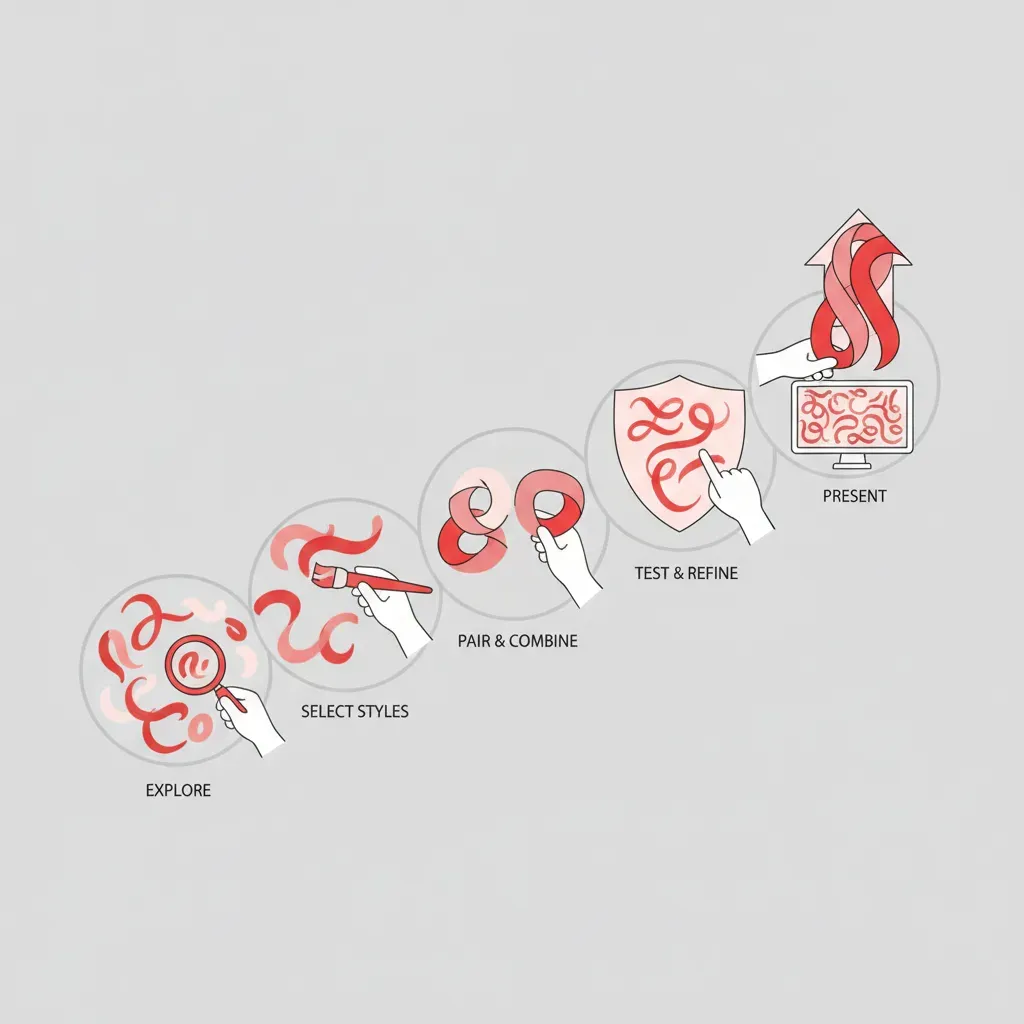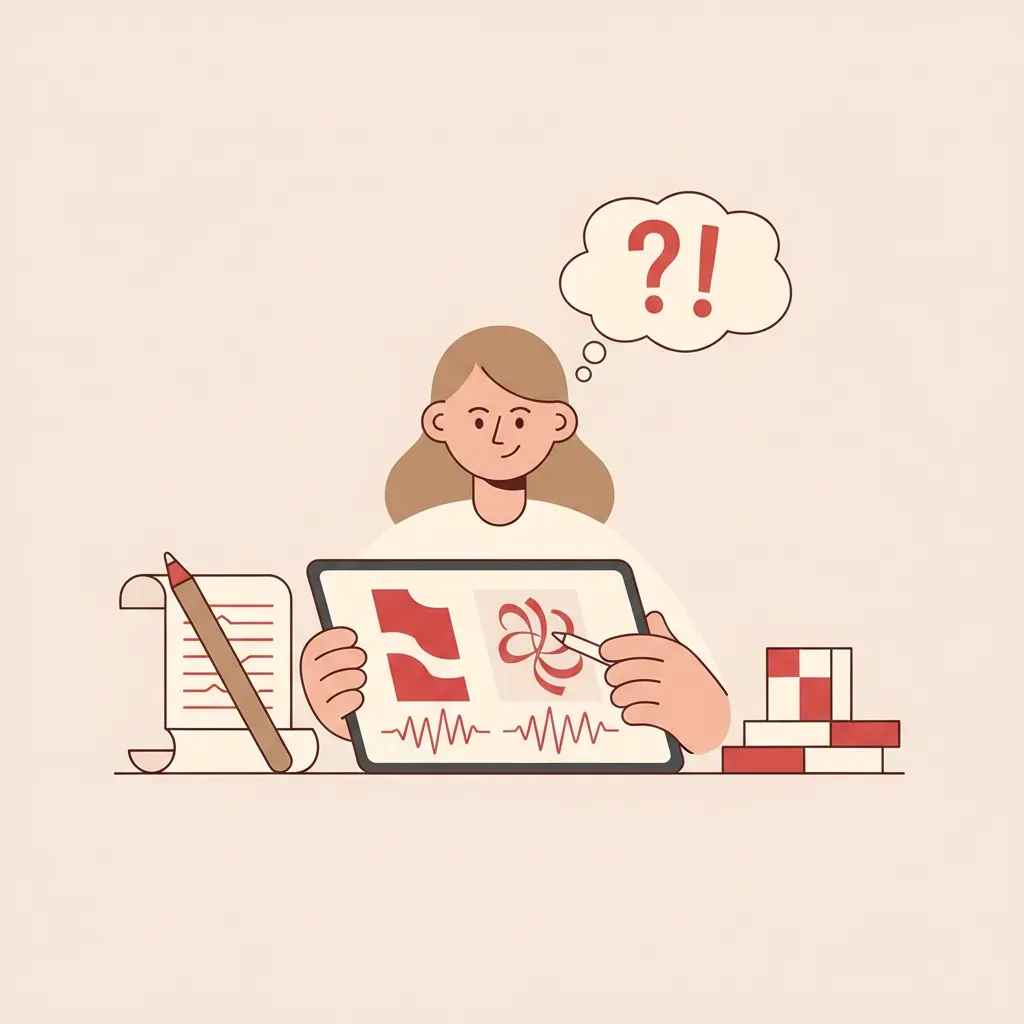
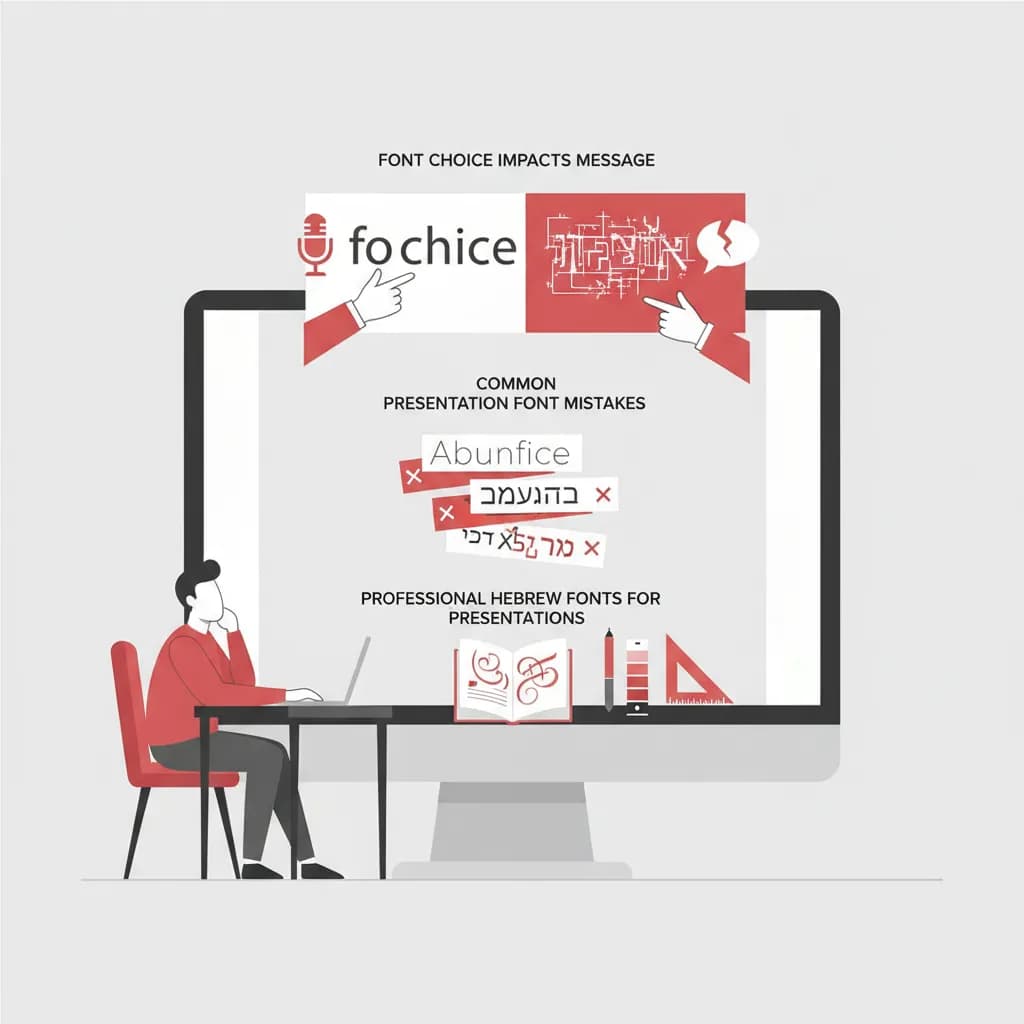
בחירת גופנים למצגת היא אחת ההחלטות הטיפוגרפיות המשמעותיות ביותר שמעצב גרפי יכול לקבל. הגופן שבוחרים משדר מסר רגשי ומקצועי עוד לפני שהקהל קרא מילה אחת – הוא מגדיר אם המצגת נראית אמינה, יצירתית, חמה או קרירה. גופנים למצגת שנבחרו נכון מגבירים את שיעור ההבנה של הצופים, מחזקים את הזהות הוויזואלית ומייצרים עקביות בין כל השקפים. לעומת זאת, גופן לא מתאים מפזר את תשומת הלב ומחליש את המסר המרכזי.
⚡ נקודות מפתח:
טיפוגרפיה היא השפה הוויזואלית של המצגת. גופנים למצגת לא נבחרים רק על בסיס אסתטיקה – הם נבחרים על בסיס המסר שהמצגת צריכה להעביר. גופן כבד ומרובע ישדר סמכות ויציבות; גופן כתב יד ישדר חמימות ואישיות; גופן גיאומטרי נקי ישדר חדשנות וטכנולוגיה.
בתחום פסיכולוגיה קוגניטיבית ידוע כי הצורה החזותית של טקסט משפיעה על האופן שבו הקורא מעבד מידע. כאשר בוחרים גופנים למצגת שמתאימים לתוכן, הקהל מעבד את המסר בצורה חלקה יותר ומרגיש שהמציג מוכן ומקצועי. כאשר הגופן "נלחם" עם התוכן – למשל, גופן שובבני במצגת פיננסית רצינית – נוצרת דיסוננס קוגניטיבי שמפריע לתקשורת.
לבחירת גופנים למצגת בעברית יש שיקולים נוספים: עברית נכתבת מימין לשמאל, ולא כל גופן מעוצב עם מנגנוני ניקוד מלאים או תמיכה בכל הסימנים הנדרשים. לכן חשוב לבחור גופן שתוכנן מלכתחילה לשפה העברית, ולא גופן לועזי שעבר התאמה חלקית.
בחירת גופנים למצגת צריכה להיות תהליך מובנה, לא אינטואיטיבי בלבד. להלן תהליך מעשי שמאפשר לקבל החלטה מושכלת:
שלב 1: הגדירו את אופי המצגת
לפני שפותחים כלל את ספריית הגופנים, שאלו: האם המצגת היא עסקית-פורמלית, אקדמית, קריאטיבית, או חינוכית? מצגת לדירקטוריון דורשת גופן שמשדר אמינות ויציבות. מצגת לסטארטאפ יכולה להרשות לעצמה גופן יותר חדשני ומרענן.
שלב 2: בחרו גופן כותרות ראשי
גופן הכותרות הוא זה שמייצר את הרושם הראשוני. הוא יכול להיות ייחודי, דרמטי, או עם אופי בולט. לדוגמה, למצגות עם אווירה מיוחדת, פונט דיפלומט מציע איזון בין יוקרה קלאסית לנגיעות מודרניות, עם משקלים מרובים שמאפשרים גמישות עיצובית.
שלב 3: בחרו גופן גוף קריא ופשוט
גופן גוף הטקסט חייב להיות קריא בגדלים קטנים יחסית ועל מסכים שונים. גופנים מסוג sans-serif – כלומר, ללא תגים בקצות האותיות – מתאימים במיוחד לטקסט גוף במצגות דיגיטליות, כיוון שהם נקיים ומדויקים על מסכי LED. גופנים עם סריף מתאימים יותר לדפוס.
שלב 4: בדקו ניגודיות ונגישות
גופן לבן על רקע בהיר, או גופן כהה על רקע כהה – שתיהן טעויות שמקשות על הקריאה. בדקו שיש ניגודיות מספקת בין צבע הגופן לצבע הרקע. לצורך נגישות, מומלץ להשתמש ב-Google Fonts כמשאב לגופנים מאושרים לנגישות.
שלב 5: בדקו עקביות לאורך כל המצגת
לאחר שבחרתם את שני הגופנים, עברו על כל שקף וודאו שהם מיושמים בעקביות. כותרות תמיד בגופן אחד, גוף טקסט תמיד בגופן השני. עקביות טיפוגרפית יוצרת תחושת מקצועיות ומאפשרת לקהל להתמקד בתוכן ולא בעיצוב.
מעבר לבחירת הגופן עצמו, ישנן מספר עצות מעשיות שמשדרגות משמעותית את השימוש בגופנים למצגת:
לדוגמה מעשית: מצגת עסקית שמציגה תוצאות כספיות לדירקטוריון תרוויח מגופן כמו פונט אופטימיסט בכותרות – גופן כתב יד חינני שמשדר חיוביות ומרומם, ומשלב אותו עם גופן sans-serif נקי לגוף. הניגוד בין השניים יוצר עניין ויזואלי מבלי לפגוע בקריאות.
צ'ק-ליסט מהיר לפני הגשת המצגת:
גם מעצבים מנוסים נופלים לפעמים לאותן מלכודות טיפוגרפיות. הנה הטעויות הנפוצות ביותר בבחירת גופנים למצגת ואיך להימנע מהן:
טעות 1: שימוש ביותר מדי גופנים שונים
שימוש בשלושה, ארבעה או חמישה גופנים שונים בגופנים למצגת אחת יוצר כאוס ויזואלי שמסיח את הדעת מהתוכן. הכלל הבסיסי: מקסימום שני גופנים – אחד לכותרות ואחד לגוף. אם רוצים גיוון, השתמשו במשקלים שונים של אותה משפחת גופנים.
טעות 2: בחירת גופנים למצגת שאינם מותקנים על מחשב אחר
גופן שמותקן על המחשב שלכם עשוי להיות מוחלף בגופן ברירת מחדל כאשר פותחים את הקובץ על מחשב אחר. הפתרון: הטמיעו את הגופן בתוך קובץ המצגת (ב-PowerPoint ניתן לעשות זאת דרך אפשרויות השמירה), או השתמשו בגופנים נפוצים. לעזרה בהתקנת גופנים, ראו איך לבצע התקנת פונטים בחינם על המחשב ב-5 דקות.
טעות 3: גופן קטן מדי לגופנים למצגת שמוקרנות
טקסט שנראה קריא על מסך הלפטופ עשוי להיות כמעט בלתי קריא כשמוקרן על מסך גדול מרחק. גופן של 18pt על מסך יכול להיראות כ-10pt מהשורה האחרונה באולם. תמיד הגדילו את גופן הטקסט מעבר למה שנראה נחוץ.
טעות 4: התאמת גופן לא נכונה לאופי הנושא
בחירת גופנים למצגת שמנוגדים לאווירה הנדרשת – גופן כתב יד שובבני למצגת משפטית, או גופן קשיח ורשמי למצגת פסטיבל ילדים – מייצרת אי-נוחות אצל הקהל, גם אם הם לא יכולים לנסח בדיוק מה מפריע. הכלל: הגופן צריך לתמוך בתוכן, לא להיאבק בו.
הכלל המקצועי הוא לא יותר משני גופנים למצגת – אחד לכותרות ואחד לגוף הטקסט. שימוש ביותר גופנים יוצר מראה לא מאורגן ומקשה על הקהל לעקוב אחרי המסר. אם רוצים גיוון ויזואלי, עדיף להשתמש במשקלים שונים (Regular, Bold, Light) של אותה משפחת גופנים.
לטקסט גוף במצגת מוקרנת, המינימום המומלץ הוא 24pt. לכותרות ראשיות – 36pt ומעלה. גופן קטן מ-24pt עלול להיות בלתי קריא לאנשים היושבים בחלק האחורי של האולם. כלל האצבע: אם אתם צריכים להתקרוב למסך כדי לקרוא את השקף, הגופן קטן מדי.
לסיכום הנקודות המרכזיות: השתמשו בלא יותר משני גופנים למצגת, שמרו על גדלים נגישים, בדקו ניגודיות, ווודאו עקביות לאורך כל השקפים. כאשר בוחרים גופן עברי ייחודי, הכניסו אותו בכותרות ושלבו אותו עם גופן נקי ופשוט לגוף הטקסט.